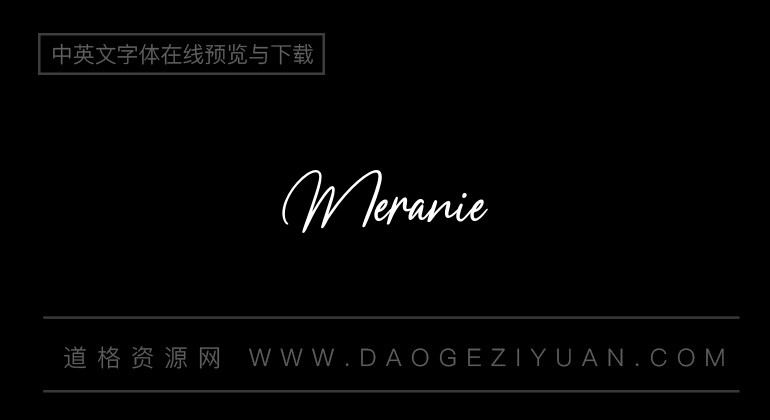
Meranie
Meranie字体是一款专为移动设备设计的非常精致的细体字体。它具有强大的可读性,清晰的细节,以及良好的可视性,适用于各种屏幕尺寸。它也具有良好的灵活性,可以用于更多的设计,从简单的文字到复杂的图标。Meranie字体非常适合用于移动应用,网站和品牌标识,可以提高用户体验。
Meranie是一款非常不错的手写艺术字体,具有很好的视觉感,适合于文化类的宣传设计、商业类品牌的广告和产品包装设计以及个性化文字排版等较多场景。